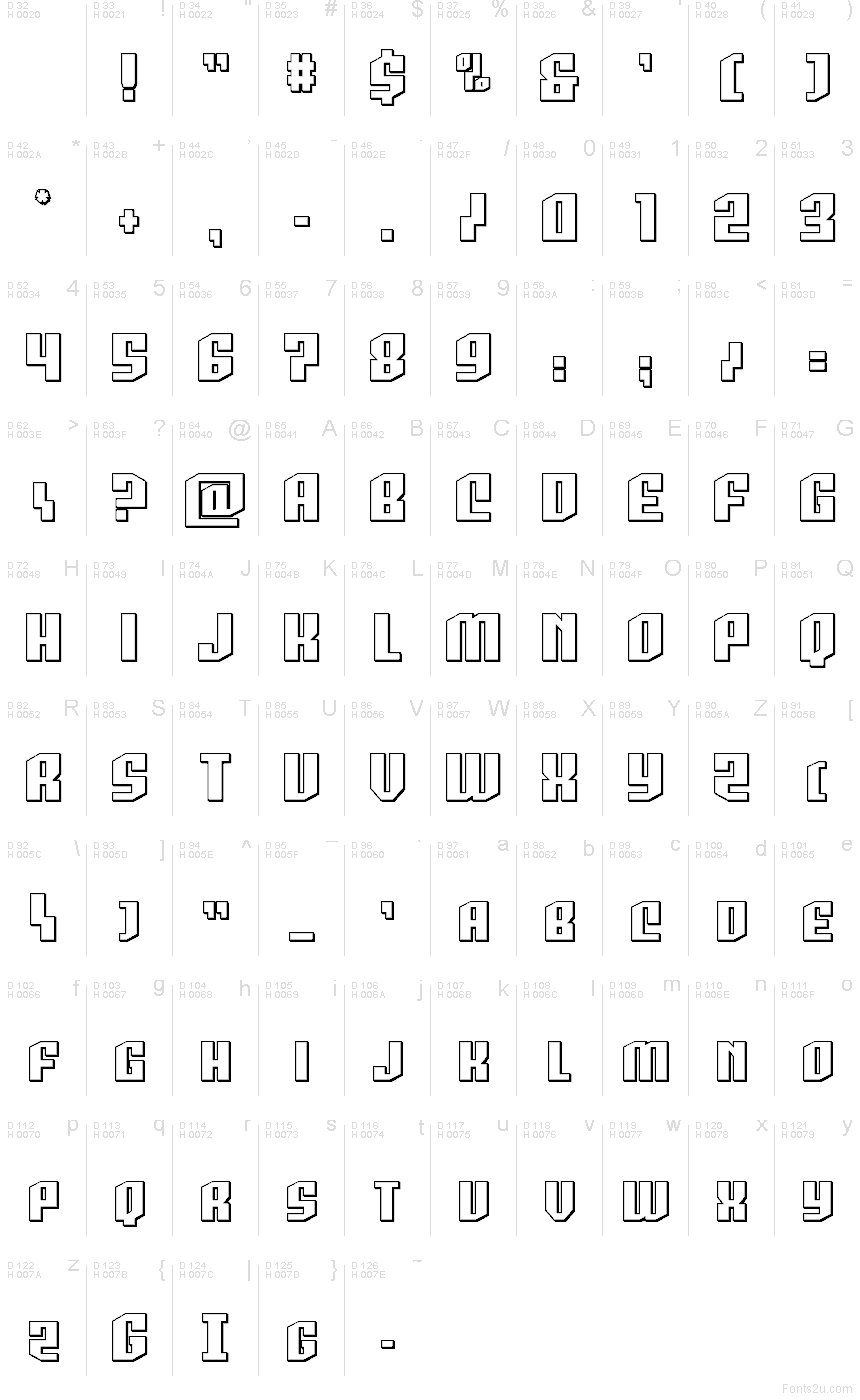
Viper Command 3D autorstwa Daniela Zadorozny (Iconian Fonts) to darmowy krój techno z wyrazistym, fazowanym konturem 3D, który przywodzi na myśl pancerne oznaczenia na kadłubie statku kosmicznego. Szerokie, kwadratowe formy i precyzyjne wewnętrzne cięcia nadają mu zdecydowany, mechaniczny rytm, podczas gdy otwarty kontur sprawia, że całość wygląda lekko, a nie masywnie.
Viper Command 3D doda natychmiastowej energii science-fiction Twoim logotypom gier, identyfikacjom drużyn e-sportowych, plakatom filmowym, miniaturom na YouTube, ulotkom wydarzeń technologicznych, nagłówkom interfejsów czy okładkom albumów. Stosuj go w dużym rozmiarze, aby zachować ostrość trójwymiarowych krawędzi, a w tekście głównym zestaw z prostym, neutralnym krojem bezszeryfowym, aby to właśnie ten darmowy font przyciągał całą uwagę.